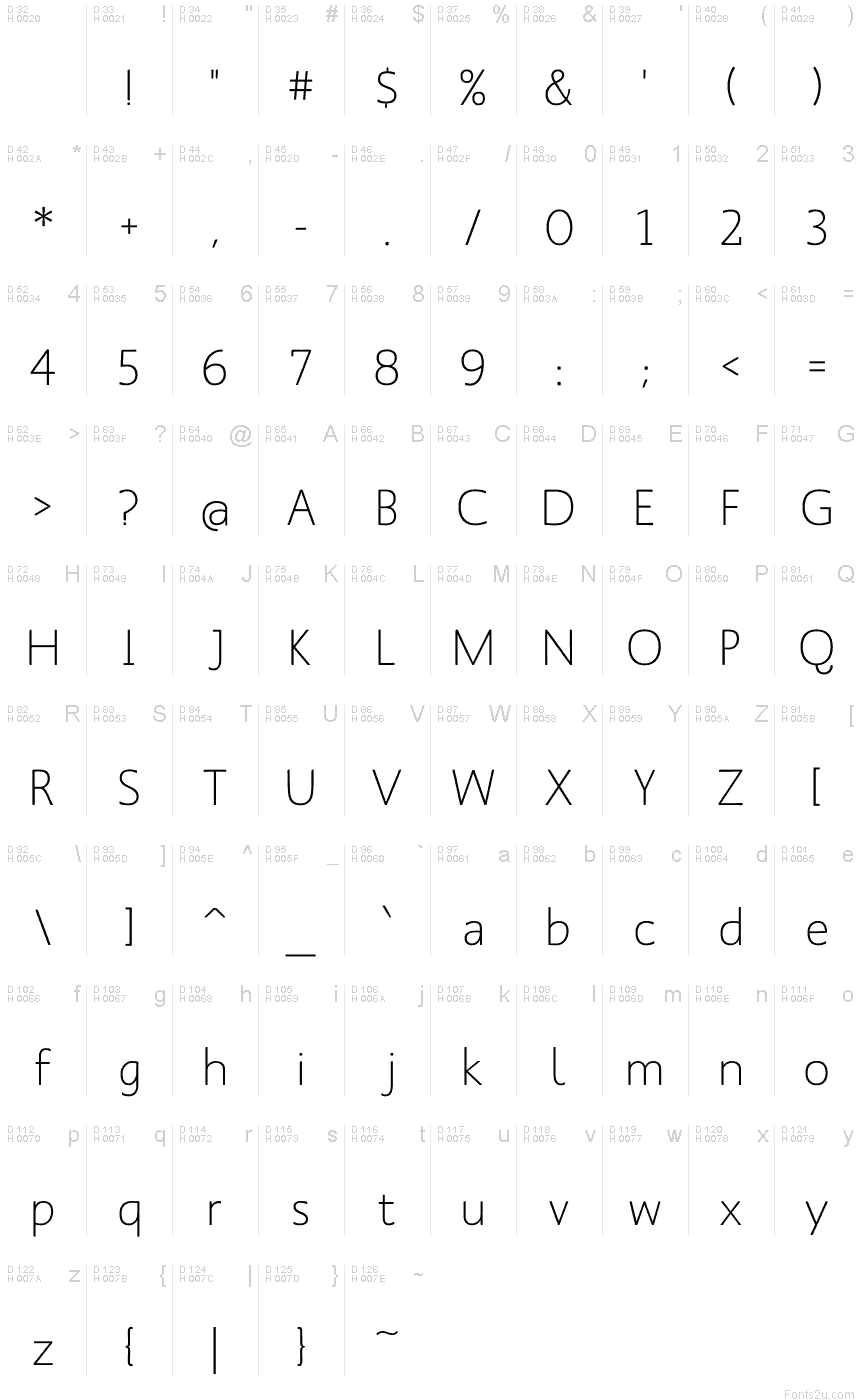
Mank Sans autorstwa M. Kleina to darmowy bezszeryfowy font o wąskich, zaokrąglonych literach i bardzo równomiernej grubości kreski. Formy pozostają proste i otwarte, a łagodne krzywizny nadają krojowi spokojny, lekki charakter, unikając przy tym dekoracyjności.
Mank Sans sprawdza się świetnie w etykietach interfejsów, krótkich podpisach, brandingu technologicznym, menu aplikacji oraz akcentach redakcyjnych, gdzie potrzebny jest stonowany font bezszeryfowy. Ten darmowy font doskonale nadaje się do takich zastosowań, ponieważ jego przejrzysta struktura i miękkie wykończenia rogów sprawiają, że tekst wygląda schludnie i nieinwazyjnie w małych blokach, na oznaczeniach czy w czystych projektach graficznych.